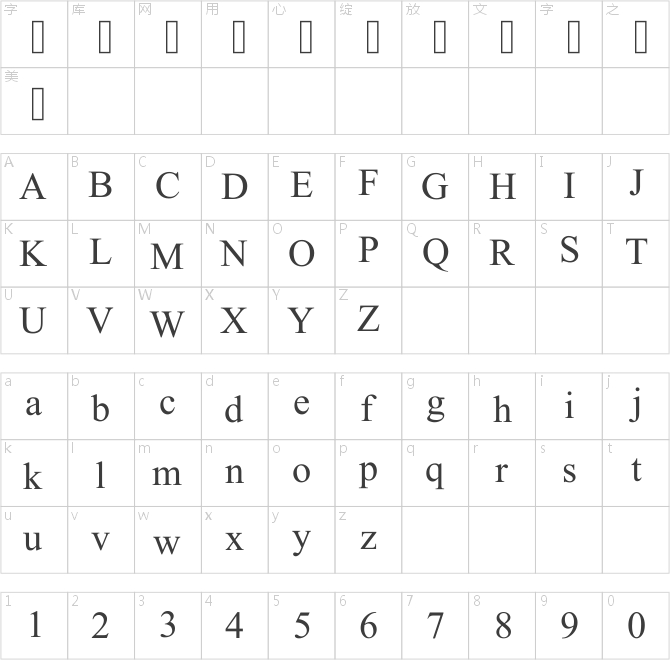
字体名称: ???????
作者版权: 迷蓝艺术
迷蓝藏文艺术
迷蓝公司董事长次仁扎西表示,公司始终把培养合格社会主义建设者和接班人作为根本任务,为广大高校毕业生提供就业择业平台,目前我公司就业带动34人,其中大学生占27人。在过去三年的时间里公司专注于藏文艺术体的研发,始终秉承以人民为中心的创作导向,坚持创作无愧于时代的优秀作品,此次面向社会共发布了14种字体,分为两种类型:传统型字体与艺术型字体,整个字体的考察、收集、研发、编辑到录入,工程为期将近三年左右,其参考了桑耶寺的石碑字体及布达拉宫的壁画字体等。